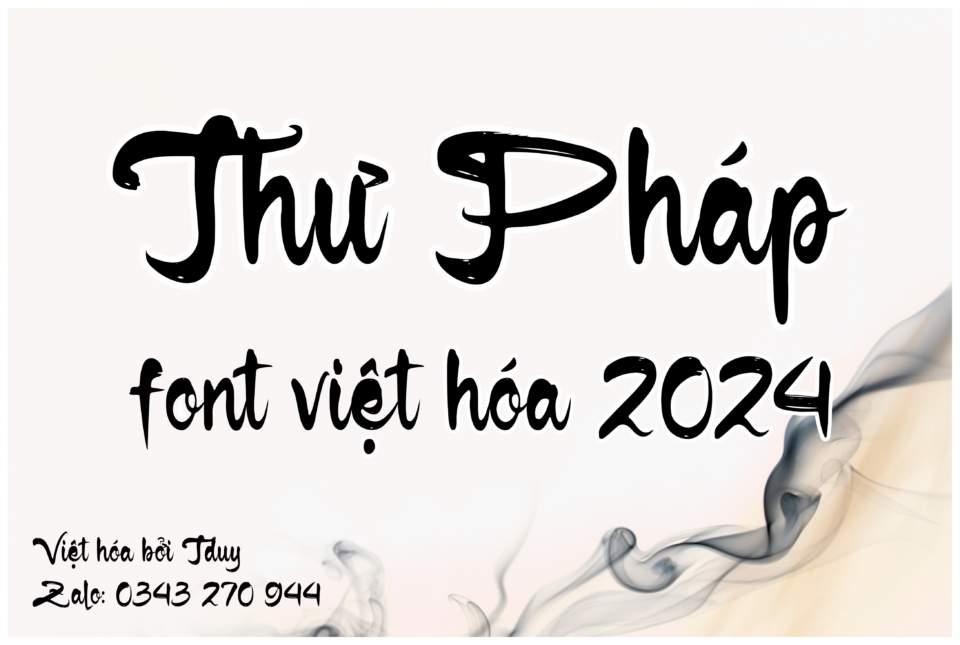
Khám Phá Vẻ Đẹp Truyền Thống Với Font việt hóa DL Thu Phap – Thư pháp: Hướng Dẫn Chi Tiết Cho Người Thiết Kế
Trong lĩnh vực thiết kế đồ họa và typography, việc tìm kiếm một Font Chữ độc đáo, mang đậm dấu ấn văn hóa luôn là ưu tiên hàng đầu. Font việt hóa DL Thu Phap – Thư pháp chính là một lựa chọn hoàn hảo, kết hợp giữa nghệ thuật viết truyền thống và công nghệ số hiện đại. Bài viết này sẽ đi sâu vào những đặc điểm nổi bật và lý do tại sao bộ font này lại trở nên phổ biến, đặc biệt trong các dự án cần sự trang trọng và tính thẩm mỹ cao, từ các ấn phẩm phục vụ học sinh, sinh viên cho đến các tài liệu chuẩn bị cho kỳ thi tốt nghiệp quan trọng. Sự tinh tế và mềm mại của font chữ thư pháp này mở ra không gian sáng tạo vô tận, giúp các tác phẩm thiết kế trở nên có hồn và ý nghĩa hơn.
Sức Hút Khó Cưỡng Của Font việt hóa DL Thu Phap – Thư pháp
DL Thu Phap không chỉ là một phông chữ; nó là sự tái hiện tinh tế của nghệ thuật thư pháp cổ điển. Được số hóa và việt hóa một cách tỉ mỉ, font này giữ trọn vẹn nét bút uyển chuyển, dứt khoát của người nghệ nhân. Đặc điểm nổi bật nhất chính là sự linh hoạt trong từng nét chữ, giúp tạo ra cảm giác tự nhiên, như thể được viết bằng cọ thật. Điều này khiến nó vượt trội hơn hẳn so với nhiều font chữ nghệ thuật khác trên thị trường, mang lại giá trị thẩm mỹ vượt thời gian. Những đường nét đậm chất Á Đông của font này đặc biệt phù hợp cho các thiết kế liên quan đến văn hóa truyền thống, lễ hội, hoặc các sự kiện mang tính học thuật cao.
Quá trình việt hóa đã giải quyết triệt để vấn đề hiển thị dấu tiếng Việt, vốn là rào cản lớn khi sử dụng các font chữ nước ngoài. Sự tương thích hoàn hảo với các ký tự như ă, â, ê, ô, ơ, ư cùng hệ thống dấu thanh rõ ràng, cân đối là điểm cộng lớn. Nhờ đó, các nhà thiết kế tại Việt Nam, dù đang làm poster quảng cáo cho trường học, thiết kế bìa sách giáo khoa, hay tạo thiệp chúc mừng, đều có thể sử dụng font thư pháp này một cách dễ dàng và hiệu quả, đảm bảo tính chuyên nghiệp và độ chính xác cao.
Ứng Dụng Đa Dạng Trong Đời Sống và Học Đường
Font DL Thu Phap thường được ưu tiên sử dụng trong các ấn phẩm mang tính văn hóa và truyền thống cao. Từ việc thiết kế bao lì xì, câu đối Tết, các ấn phẩm kỷ niệm ngày khai giảng hay bế giảng, cho đến việc tạo logo cho các thương hiệu muốn nhấn mạnh yếu tố truyền thống Việt Nam. Đây là công cụ không thể thiếu để tạo ra sự khác biệt và thu hút thị giác mạnh mẽ. Khi áp dụng vào các tài liệu học tập, đặc biệt là các môn liên quan đến Văn học hay Lịch sử, font này giúp tạo không khí trang trọng, kích thích sự hứng thú của học sinh.
Đối với học sinh cấp 3 chuẩn bị cho kỳ thi tốt nghiệp quan trọng, việc in ấn tài liệu hay làm các dự án sáng tạo cũng cần đến sự chăm chút về mặt hình thức. Mặc dù không phải là font chữ chính thức cho văn bản hành chính, DL Thu Phap lại lý tưởng cho các tiêu đề, banner giới thiệu sự kiện hoặc các bản tin trường học. Nó giúp nâng cao chất lượng thị giác của bất kỳ sản phẩm đồ họa nào, biến một thông báo đơn thuần thành một tác phẩm nghệ thuật thu hút người đọc.
Nghệ Thuật Typography và Vai Trò Trong Phát Triển Sáng Tạo
Việc tiếp xúc với các font chữ nghệ thuật như font việt hóa DL Thu Phap còn mang lại lợi ích giáo dục đáng kể. Nó khuyến khích học sinh, sinh viên tìm hiểu về nghệ thuật thư pháp và typography, từ đó phát triển kỹ năng thẩm mỹ và tư duy sáng tạo. Các hoạt động ngoại khóa liên quan đến thiết kế poster hay viết thư pháp số sử dụng font này có thể trở thành bài học trực quan sinh động về văn hóa và ngôn ngữ. Bộ font này không chỉ là công cụ mà còn là cầu nối giữa truyền thống và công nghệ cho thế hệ trẻ, giúp các em trân trọng hơn nét đẹp của ngôn ngữ viết.
Một mẹo nhỏ khi sử dụng font chữ thư pháp này là kết hợp nó với các font chữ sans-serif hoặc serif đơn giản khác cho phần nội dung chi tiết. Điều này giúp cân bằng tổng thể thiết kế, tránh làm người đọc bị rối mắt và đảm bảo tính dễ đọc của văn bản. Do tính chất nghệ thuật và độ phức tạp của nét chữ, DL Thu Phap nên được dùng chủ yếu cho tiêu đề, các câu trích dẫn quan trọng, hoặc các điểm nhấn chính trong thiết kế, nơi mà vẻ đẹp của nghệ thuật chữ viết có thể được phô diễn tối đa. Việc này đặc biệt hữu ích khi thiết kế các tài liệu hướng dẫn ôn thi hoặc các ấn phẩm kỷ niệm ngày tốt nghiệp, cần sự kết hợp hài hòa giữa thông tin và thẩm mỹ.
Tóm lại, Font việt hóa DL Thu Phap – Thư pháp là tài sản vô giá cho bất kỳ ai hoạt động trong lĩnh vực thiết kế hay giáo dục, từ sinh viên đến chuyên gia. Nó không chỉ cung cấp một giải pháp typography chất lượng cao mà còn góp phần bảo tồn và phát huy giá trị nghệ thuật thư pháp Việt. Việc sử dụng Font Chữ này chắc chắn sẽ làm cho các dự án của bạn trở nên nổi bật và ý nghĩa hơn bao giờ hết. Đừng ngần ngại tải về và trải nghiệm sức mạnh của nghệ thuật viết tay trong kỷ nguyên số, mang lại chiều sâu văn hóa cho mọi thiết kế.